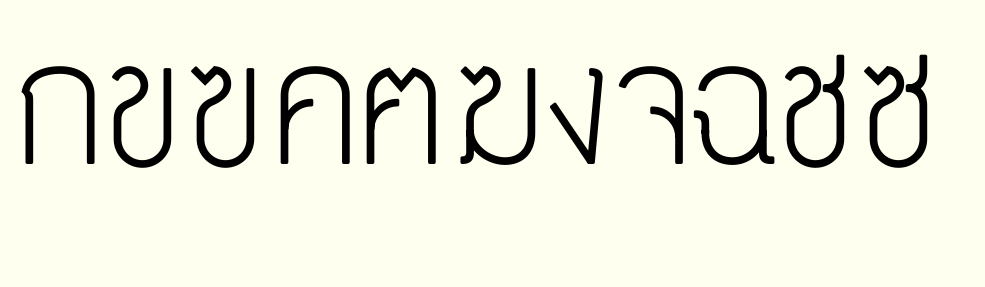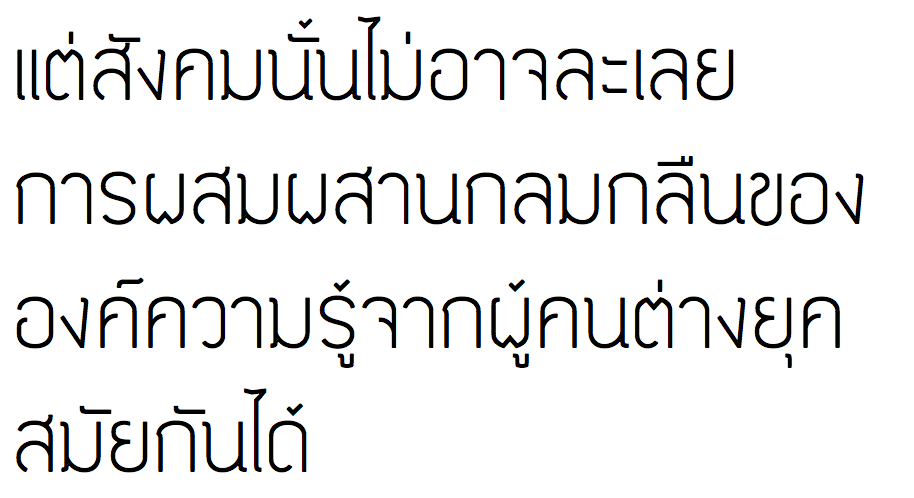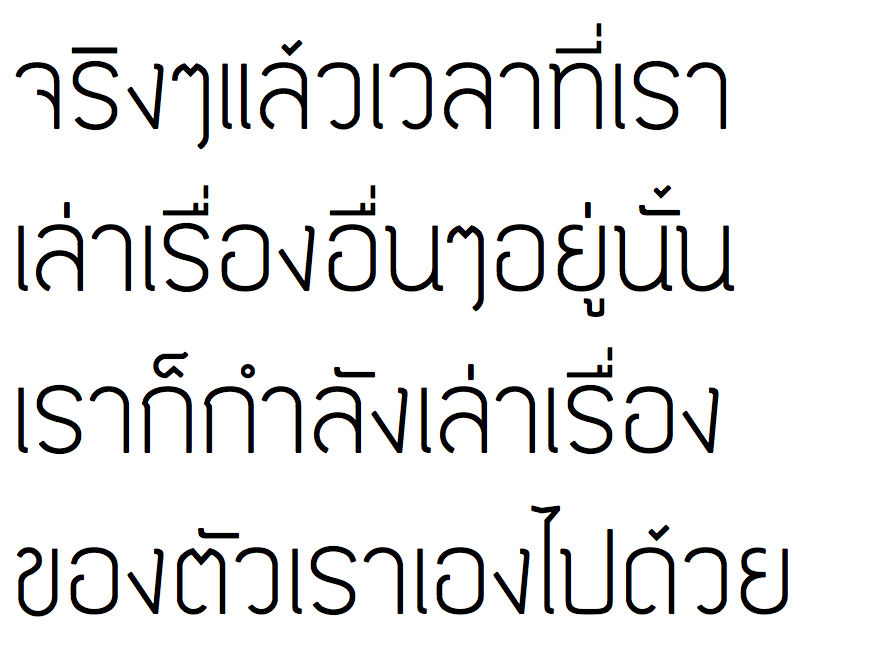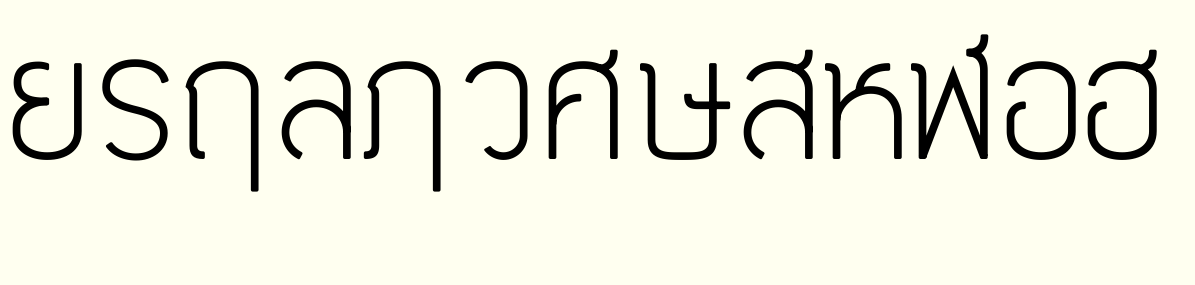
พอดีทำฟอนต์ตัวใหม่(ยังคิดชื่อไม่ออกเหมือนกัน)  ที่ร่างแบบไว้สักพัก
ขึ้นโครงสร้าง ชุดภาษาไทย แต่ยังไม่ได้จัดทำอะไรกับมันเลยเอามาฝากให้ช่วยกันหน่อยครับ
เลขไทยนี่ยังแปลกตาจริงๆ ครับโดยเฉพาะ ๕ กับ ๗
ส่วนตัวทั่วไปก็ ฎ พอลดทอนให้มันเกลี้ยง เลยดูตัวเดียวเดี่ยวๆ เหมือน ฎ เลยนะ ขยักเดียว
เปลี่ยนชื่อเป็น อีดีเป็นสุข ครับ
ลองเอามาเรียงเป็นประโยคครับ
คิดว่าหลังสงกรานต์คงจะเริ่มทำตัวหนา แล้วก็ปรับแก้กันต่อไปขอรับ
เหลือตำแหน่งวรรณยุกต์เท่านั้นเอง
เอสขออนุญาติใช้ตำแหน่งวรรณยุกต์ล่างแบบนี้นะครับ เพราะตั้งใจให้เป็นแบบนี้
มันอาจจะขัดตาไปบ้าง ตรงไม้เอก บน ม.ม้า น.หนู นี่แหละ
• ชื่อฟอนต์ : EDPenSook
ตอนนั่งทำฟอนต์ตัวนี้ มันคำถามกับตัวเองว่า ทำไปทำไม ปวดหลังมากเลย อดหลับอดนอนด้วย
แล้วเอสก็ได้คำตอบกับตัวเองว่า
ตอนทำฟอนต์มันเป็นช่วงที่"เป็นสุข"กับชีวิตจริงๆ
เลยเป็นที่มาของชื่อฟอนต์ตัวนี้ครับ
version regular วรรณยุกต์ขัดตา ตามใจคนทำ 555555
version NormalTone วรรณยุกต์ปรกติ
สรุปทำวรรณยุกต์มัน 2 แบบเลย ทั้งขัดตาตามใจคนทำ และปรกติทั่วไปครับ  :30: